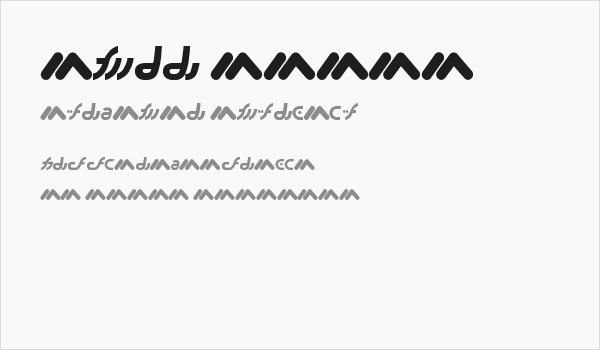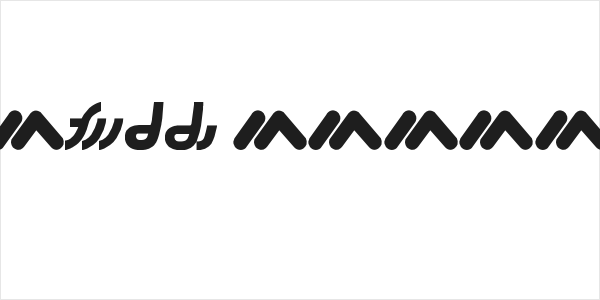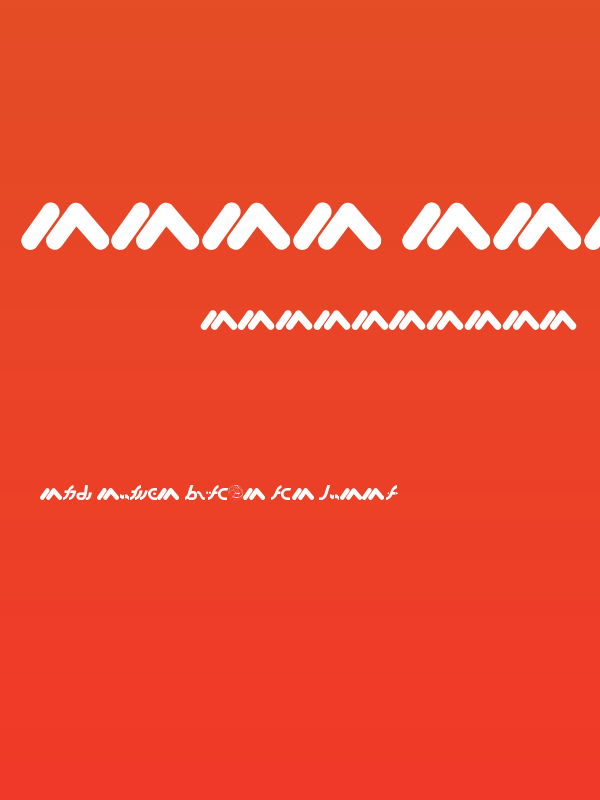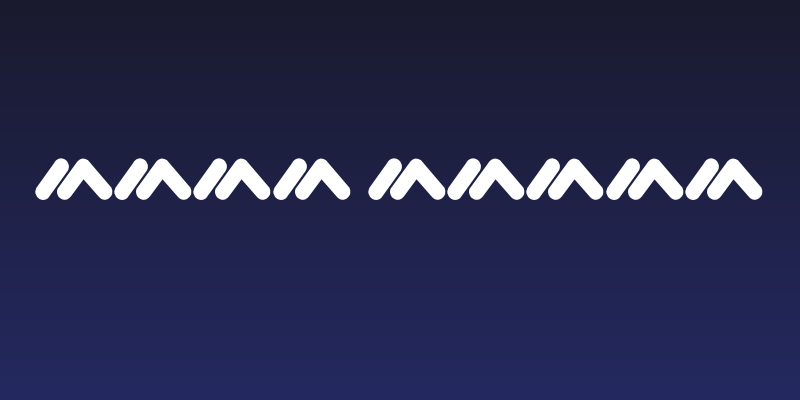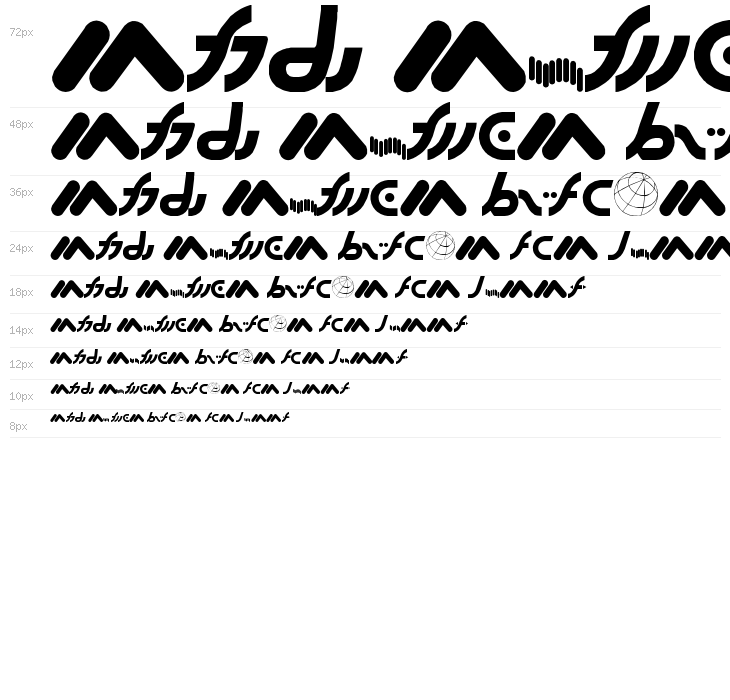
Lide 106.9 Font
| Stile generale | Futuristic, Abstract |
| Caso d'uso | Logos, Artistic displays, Experimental design |
| Progetti proposti | Ideal for experimental design projects, futuristic branding, abstract art pieces, and creative digital media. |